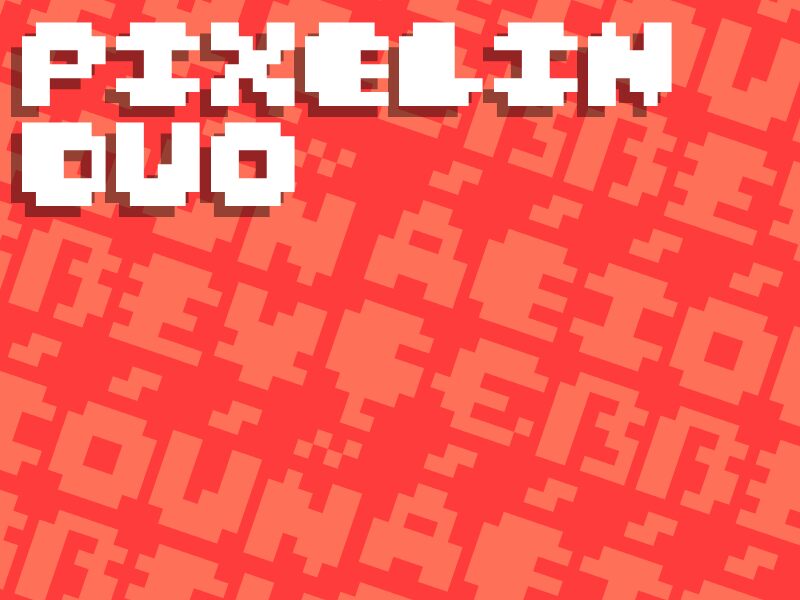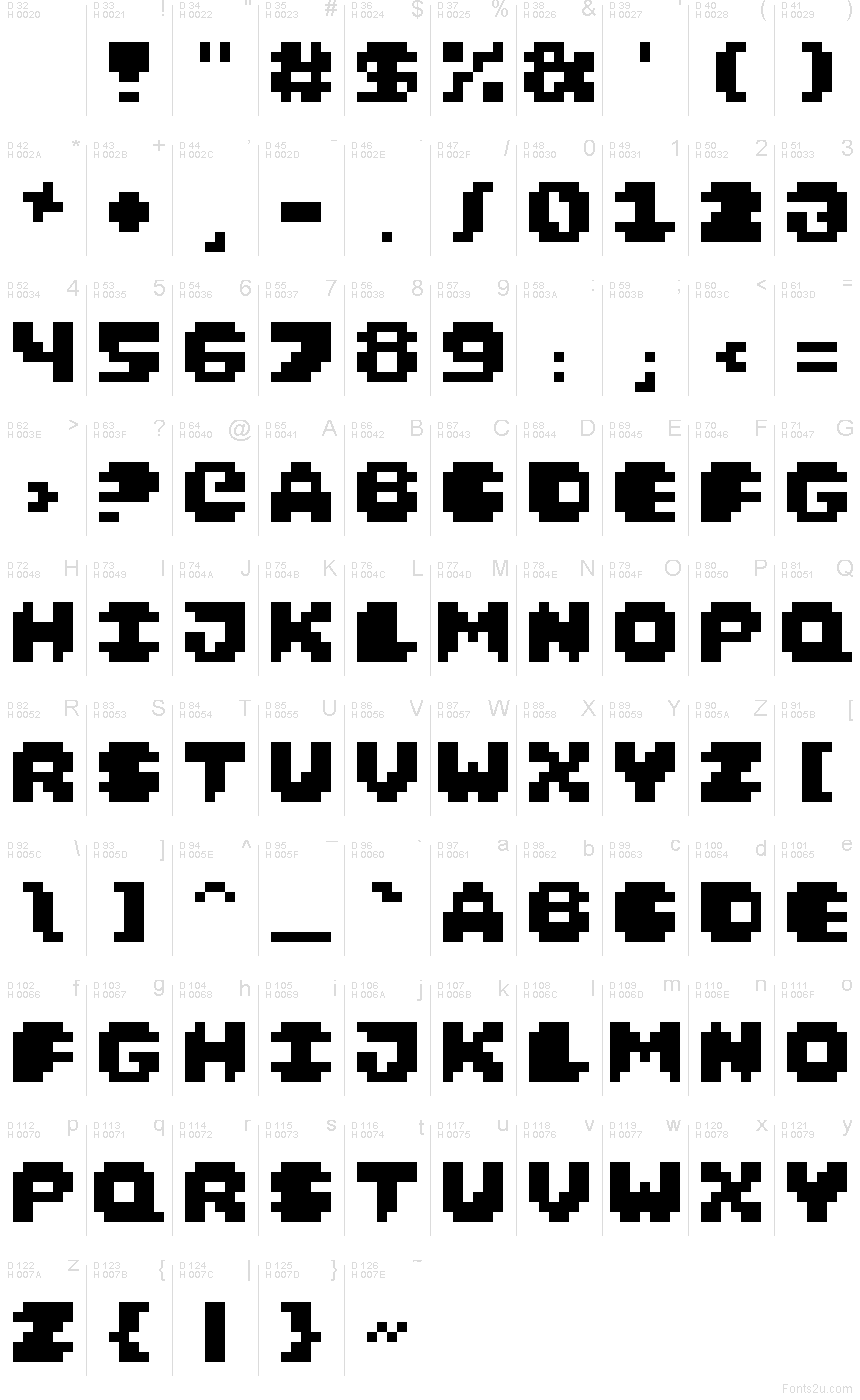
Pixelin Duo je bezplatné pixelové písmo složené z masivních obdélníkových tahů a ostrých pravouhlých zatáček. Jeho písmena mají neotesanou geometrii rané obrazovkové grafiky, se schodovitými okraji, čtvercovými mezerami a kompaktními tvary, které vytvářejí hustou, mechanickou texturu a rigidní rytmus připomínající strojové displeje.
Retro hry a digitální technologie jsou pro toto písmo nejjasnějším tématem, díky čemuž se hodí pro herní rozhraní, arkádové plakáty a obaly elektronické hudby. Může také tvarovat předměty pro programátorské akce, kde opakovaná mřížková konstrukce může připomínat sprity, schémata obvodů a další nízkorozlišené obrázky, namísto toho, aby působilo jako neutrální text.
Pixelin Duo